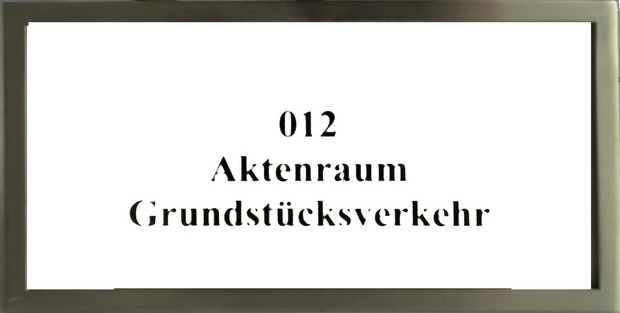
Suche diese Schriftart
wir haben gerade ein Haus aus den 50er Jahren saniert und wollten gerne die Türschilder in der originalen Schriftart gestalten. Leider ist es nicht so leicht die richtige Schriftart zu finden. Aber vielleicht kennt ja jemand die Gesuchte.
Times würde aber zeitlich nicht in die 50er Jahre passen, oder? Sie war ja schließlich eine Zeitungsschrift und kam erst mit PostScript auf alle Computer. Ich kann mir auch nicht vorstellen, daß man Türschilder im Bleisatz gesetzt hat. Kann man anhand der Original-Schilder vielleicht erkennen, mit welcher Technik diese hergestellt wurden?
Egal, mit welcher Technik die Schilder gemacht wurden, die Times hat es von Blei bis Rechner meines Wissens in allen Technologiestufen gegeben, sie war — eben weil es eine Zeitungsschrift ist — immer mit unter den am besten ausgebauten und verfügbaren Schriften.
Das mit der Times kommt ziemlich gut hin. (manchmal sieht man den Wald vor lauter Bäumen nicht....)
Wir haben leider nur diese eine Aufnahe des Türschildes mit den ausgefransten Buchstaben. Dachte deshalb es wäre ein alte Stempelschrift....
Ich denke dass die Aufnahme überstrahlt ist, evtl. durch eine transparente Kunststoffabdeckung vor dem Schild, und die Schrift in Wirklichkeit gar nicht ausgefranst ist.